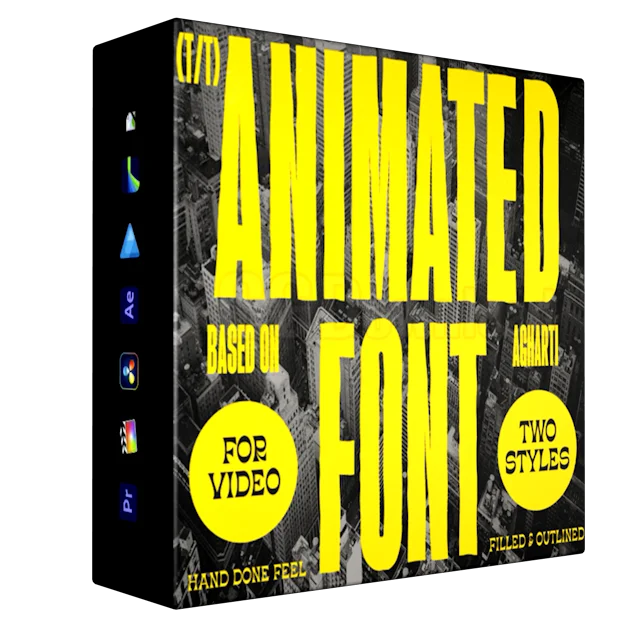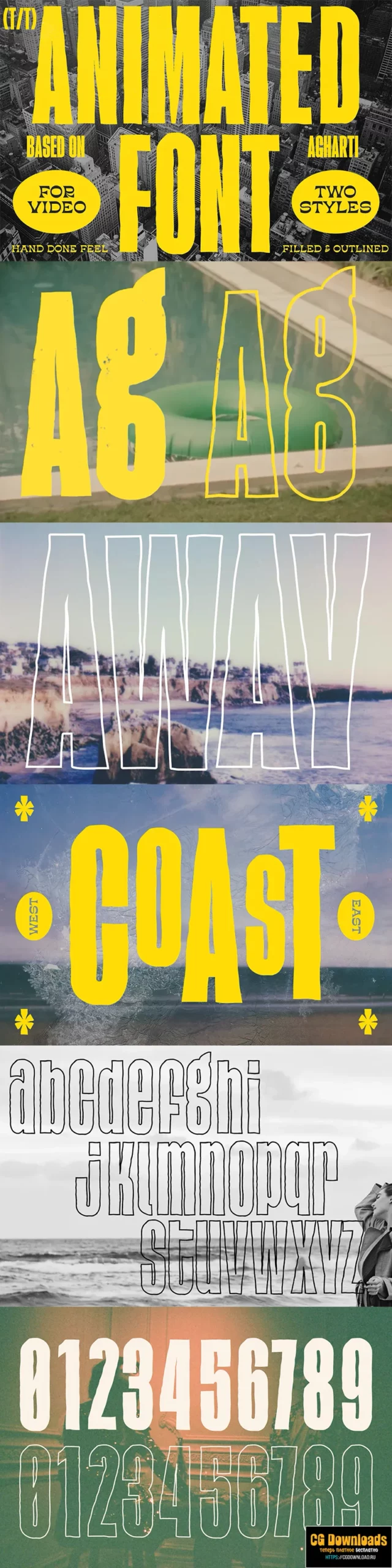
Animated Font Agharti
Этот анимированный шрифт передает все правильные нотки ностальгии по ретро-винтажу летних каникул. И он поставляется в двух стилях. заполнены и очерчены. Он основан на шрифте Agharti и получил некоторую индивидуальность в своей анимации. Он имеет текстуру пыли и царапин и покадровые анимированные дефекты. Этот анимированный шрифт хорошо подходит для любого видеопроекта, от Instagram и TikTok до фирменных видеороликов.
• 2 Styles filled & Outlined
• Caps
• Lowers
• Numbers
• Punctuation